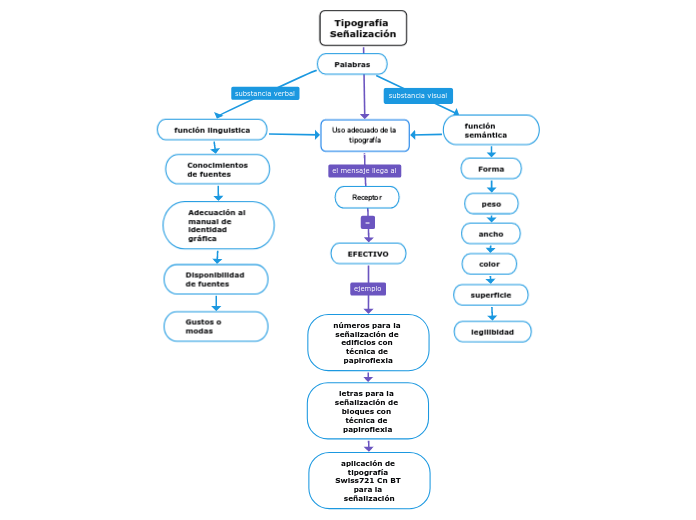
Tipografía Señalización
Conocimientos de fuentes
Adecuación al manual de identidad gráfica
Disponibilidad de fuentes
Gustos o modas
función semántica
Forma
peso
ancho
color
superficie
legilibidad
Palabras
función linguistica
Tipografía Señalización
Uso adecuado de la tipografía
Receptor
EFECTIVO
números para la señalización de edificios con técnica de papiroflexia
letras para la señalización de bloques con técnica de papiroflexia
aplicación de tipografía Swiss721 Cn BT para la señalización